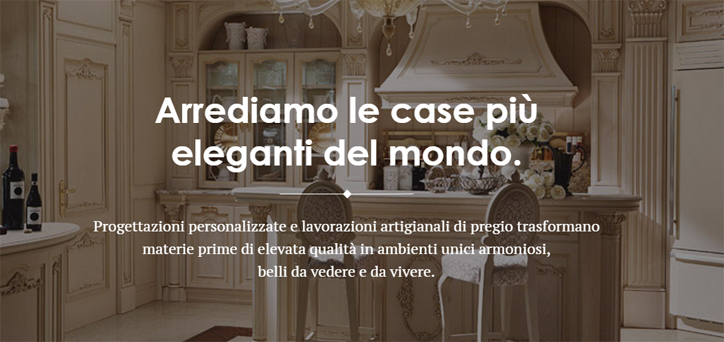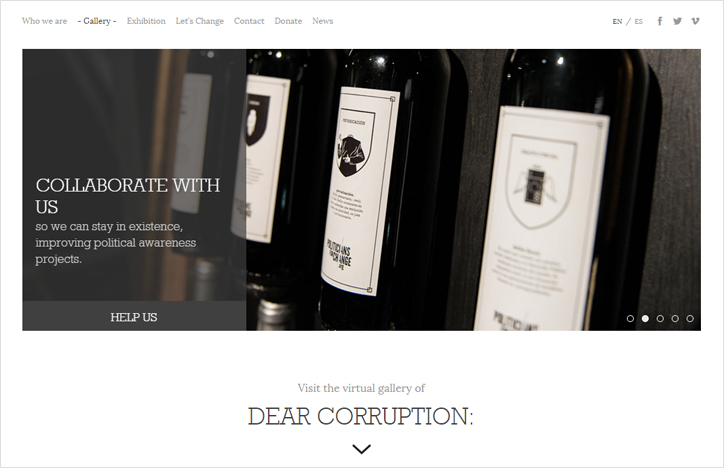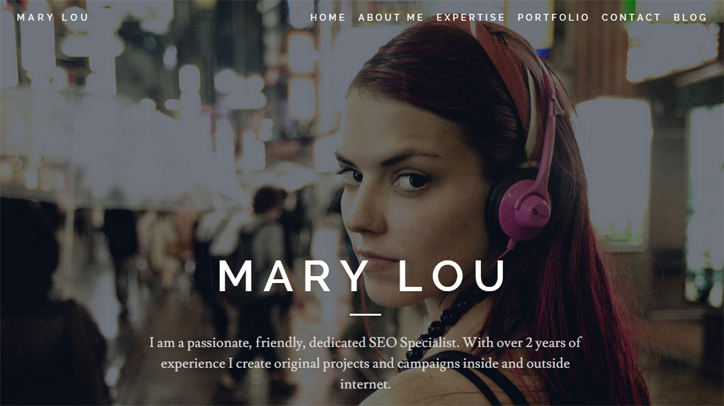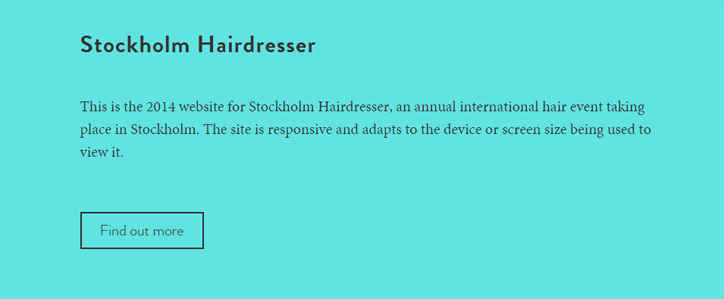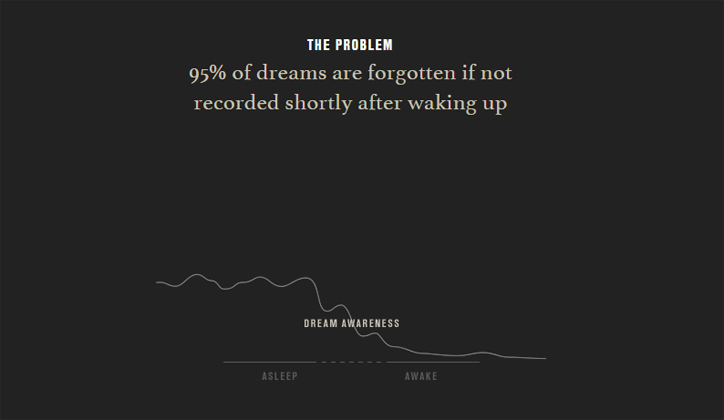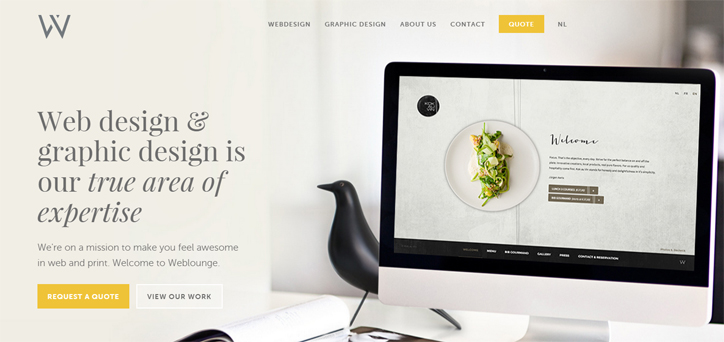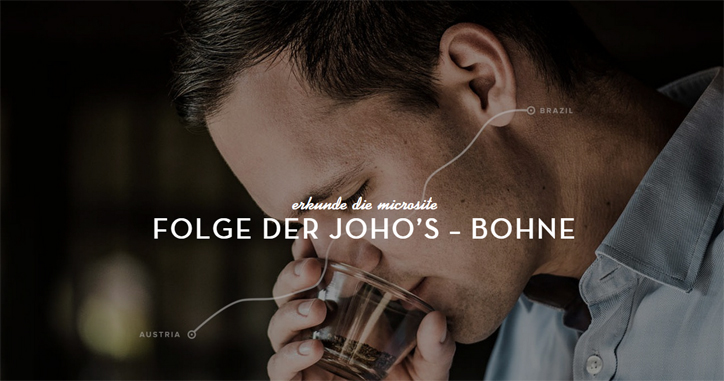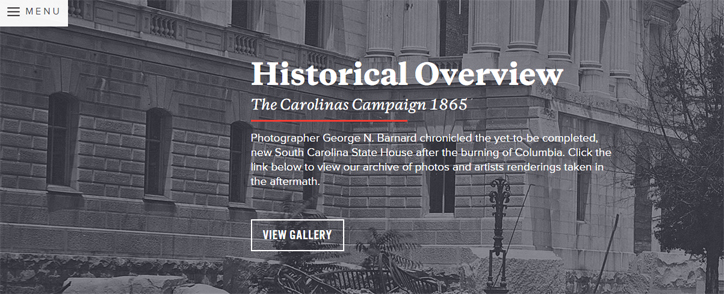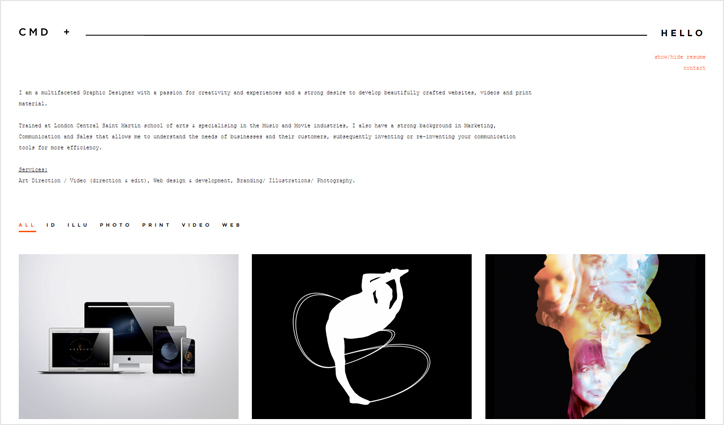
Web Tasarımcılar İçin Font Kombinasyon Önerileri
İlham veren font kombinasyon önerileri, web tasarımcıların projeleri için yazı tipi seçmelerini ve başarılı projeler üretmelerini kolaylaştıracaktır. Yeni bir projeye başladıklarında web tasarımcıların karar vermekte zorlandığı ve zaman alan konulardan biri uygun bir yazı fontu bulmak oluyor. Yazı fontuna karar vermek birçok nedenden dolayı zorlayıcı olabiliyor. Bu nedenlerin başında ise tasarıma uyabilecek binlerce fontu arasından seçim yapmak geliyor. Tasarımda dikkat çeken bir harf karakteri bulmak için defalarca yeniden başlamanız gerekebilir. Birçok tasarımcı bu konuda dertli iken yardımı dokunabilecek bir kaynak bulmak zor. Google Fonts, harf tipi seçimine yardımcı olsa da iş bununla bitmiyor. Tasarımı mükemmelleştirmek için farklı yaklaşımlardan faydalanmak da gerekiyor. Tasarımcıların işlerini kolaylaştıracak bu yaklaşımlardan biri font kombinasyonu. Birçok tasarımcı yazı tiplerini birlikte kullanarak yeni ve sıra dışı kombinasyonlar elde edebiliyor. Aşağıda tasarımlarınıza ilham verecek font kombinasyon önerilerini, kullanıldıkları web sitesi örnekleri ile birlikte inceleyebilirsiniz. Super Grotesk & Minion Pro Farklı yazı tipleri hem sade hem dikkat çekici bir tasarım elde etmek için kullanılabilir. Örneğin bu tarz bir tasarım için Sans Serif ve Sans One fontları oldukça uygun. Ape Unit web sitesinde Serif yazı tipi Minion Pro, Sans Serif yazı tipi Super Grotesk ile birlikte kullanılmış. Super Grotesk’in modern, ince ve daha hafif çizgisiyle bir araya gelen Minion Pro ile minimalist bir tarz ortaya çıkmış.
web tasarım Montserrat & Courier New Claire Marion, web sitesinde Montserrat ve Courier New font kombinasyonunu tercih ederek minimalist bir görünüm elde etmiş. Montserrat web tasarımda şıklığı, sadeliği ve modern görünümü ile oldukça kullanılan bir Sans-Serif yazı tipi. Courier New ise daha eski bir görünüme sahip ve daktilo yazılarını andırıyor ve çok sık kullanılmayan bu yazı tipi modern çizgilere sahip bir fontu ile oldukça uyumlu olabiliyor. web tasarımda font Rockwell Standard & Lora Politicians for Change birbirinden çok farklı olmayan iki fontu bir araya bir arada kullanarak tasarımda başarıyı yakalamış görünüyor. Slab Serif yazı tipi olarak sınıflandırılan Rockwell Standard ana başlıklarda kullanılırken, Serif yazı tipleri arasında yer alan Lora alt başlıklarda yer almış. tasarımda font seçimi Copernicus & Proxima Nova Oldukça az kullanılan fontlardan biri olan Copernicus, Burning of Columbia web sitesinde başlıklarda yer alırken; Proxima Nova ise metinlerin geri kalanında kullanılmış. Bir klasik Serif ve Sans Serif kombinasyonu olarak iki font birbirini başarılı bir şekilde tamamlamış. Copernicus ile başlığa ilgi çekilmesi amaçlanırken, Proxima Nova’nın paragrafları daha iyi göstermesinden faydalanarak okunabilirlik artırılmış. web tasarımda font seçimi Century Gothic & PT Serif Century Gothic ve PT Serif yazı tipleri de bir Sans Serif ve Serif kombinasyonu olarak oldukça başarılı. Ağırlıklı olarak paragraflarda kullanılan PT Serif şık ve modern bir görünüm katarken, Century Gothic uyumlu bir şekilde onu tamamlıyor. tasarım fontları Kaufmann & NeutraDemi Kaufmann ve NeutraDemi farklı ve göze hoş gelen bir kombinasyon olarak kullanılabilir. Modern Sans Serif yazı tiplerinden biri olan NeutraDemi tasarıma bir tarz ve şıklık; Kaufmann ise el yazısına benzerliği ile zarafet katıyor. İki font birbirine çok uzak olmasına rağmen uygun tasarımlarda kullanıldığında başarılı sonuçlar verecektir. web tasarım için yazı tipleri Brandon Grotesque & Minion Pro Bu örnekte Brandon Grotesque başlıklarda kullanılmış, Minion Pro ise daha küçük puntolu gövde metinlerinde kullanılmış. web tasarım font kombinasyonları Playfair Display & Museo Sans Tasarımda abartıya kaçmadan şık, zarif ve göz alıcı bir tarz yakalamak zor olabiliyor. Playfair Display ve Museo Sans yazı tiplerinin birlikte kullanımı abartısız ve göz alıcı bir kullanıma güzel bir örnek olmuş. Playfair Display’in abartılı gelebilecek kıvrımları Museo Sans’ın modern ve sadeliği ile dengelenmiş. web tasarım için font kombinasyonları Raleway & Lusitana Raleaway ve Lusitana fontları bir araya getirilerek sıcak ve sade bir tasarım ortaya koyabilirsiniz. Serif ve Sans Serif fontlarının bir araya getirilmesiyle ortaya çıkan bu kombinasyonu tipografik görünümde şıklık ve sadelik yakalamak için kullanabilirsiniz. tasarımda yazı tipi Alternate Gothic & Georgia Minimalist ve flat tasarımların en büyük özelliği olan sadeliği Alternate Gothic ve Georgia yazı tiplerinin kombinasyonu ile yakalayabilirsiniz. Özellikle ürün merkezli ve abartılı tasarım detaylarıyla ziyaretçilerin dikkatinin dağılmasını engellemek için uygun bir tercih olacaktır. web tasarım yazı tipi seçimi Helvetica & Garamond Helvetica ve Garamond sade tasarımlar için çok uygun ve şık duran bir diğer kombinasyon. Helvetica sadeliği ve kolay okunabilirliği ile çok tercih edilen bir yazı tipi ve biraz daha gösterişli olan Garamond ile birlikte kullanıldığında abartıya kaçmayan, kullanıcının dikkatini dağıtmayan bir tasarım ortaya çıkıyor. web tasarımda yazı tipi Cubano & Nunito Cubano ve Nunito birlikte kullanıldığında benzersiz bir tasarım ortaya çıkıyor. Bu göz alıcı kombinasyondaki yazı tiplerinin ikisi de Sans Serif. Birbirine çok benzeyen yazı tiplerinin kullanımı her zaman iyi sonuçlar doğurmasa da bu örnek oldukça başarılı. web tasarım font seçimi Source Sans Pro & Times New Roman artık nadir kullanılan bir yazı tipi. Tasarımcılar daha yeni ve modern fontlarını tercih ediyor. Yine de Times New Roman kolay okunabilir metinler oluşturmak için oldukça kullanışlıdır. Source Sans Pro daha sık kullanılan bir yazı tipi. Times New Roman ile birlikte kullanıldığında modern çizgide ve kullanıcıların dikkatini dağıtmayan sade ve şık bir tasarım ortaya çıkacaktır. web tasarımda yazı tipi seçimi Nimbus Sans Condensed & Athelas Şık ve seçkin bir tasarım oluşturmak için kullanılabilecek font kombinasyonlarından biri de Nimbus Sans Condensed ve Athelas. Athelas modern ve klasik bir görünüm sunarken; Nimbus Sans Condensed sıkıştırılmış, kısa ve kalın bir yazı tipi olarak dikkat çeker. İki fontun zıtlığı ilgi çekici bir tasarım elde etmek için kullanılabilir. web tasarım fontları Web tasarımcılar özgün ve ilgi çekici tasarımlar ortaya çıkarmak için ilham veren font kombinasyonlarından faydalanabilir.